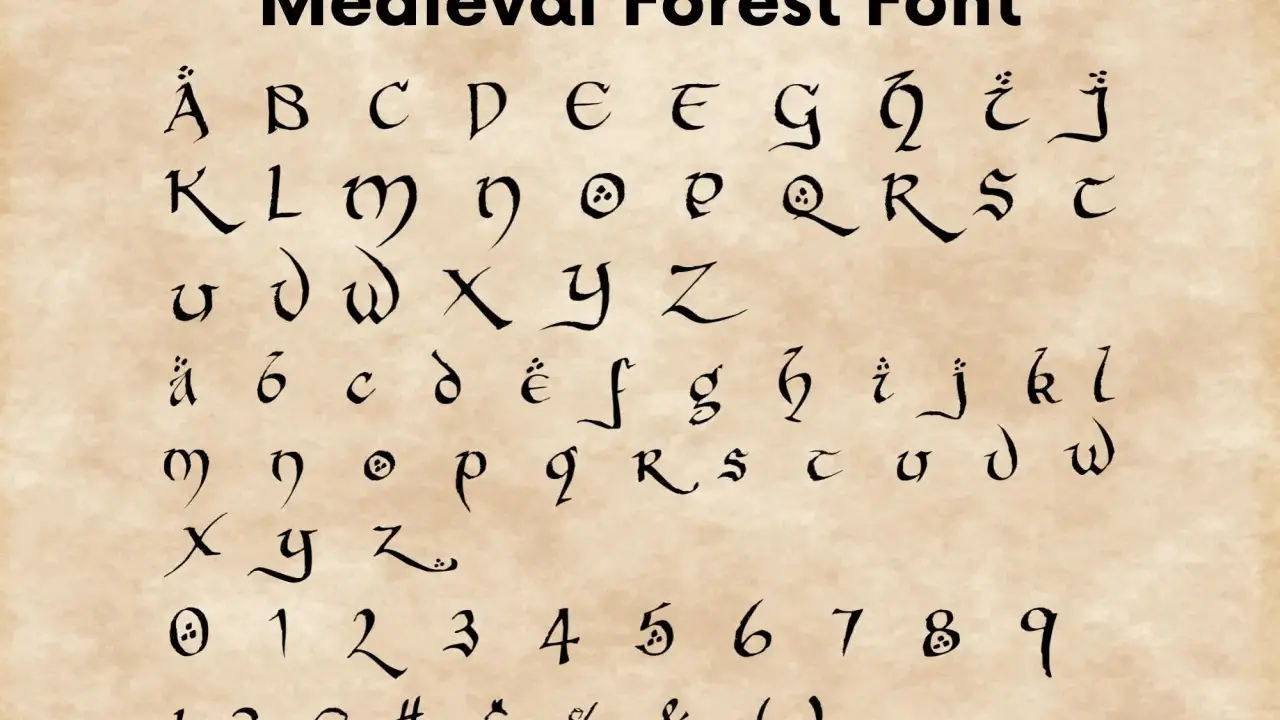
To, co potocznie bywa opisywane jako średniowieczna czcionka, w praktyce jest całym zestawem krojów inspirowanych dawnym pismem rękopiśmiennym: od ciężkich, gotyckich liter po lżejsze i bardziej dekoracyjne warianty. Taki styl potrafi od razu zbudować klimat tradycji, tajemnicy albo luksusu, ale równie szybko może osłabić czytelność, jeśli użyje się go bez wyczucia. Poniżej pokazuję, jak rozumieć ten typ pisma, czym różnią się jego odmiany i kiedy naprawdę warto po niego sięgnąć.
- To nie jeden krój, lecz cała rodzina pism inspirowanych historycznymi skryptami i gotycką tradycją.
- Najlepiej działa w krótkich hasłach, logotypach, tytułach i plakatach, a nie w długich akapitach.
- Różne odmiany dają inny efekt: od bardziej historycznego po dekoracyjny i nowoczesny.
- Przy wyborze fontu liczą się także polskie znaki, licencja i jakość odstępów między literami.
- Najczęstszy błąd to przesada: zbyt dużo ozdobników, za mały rozmiar i za długi tekst.
Czym naprawdę jest gotycki krój i skąd bierze się jego siła
W projektach użytkowych wolę mówić o kroju pisma niż o „czcionce”, bo to precyzyjniejsze, ale w praktyce sens jest prosty: chodzi o styl, który czerpie z ręcznych zapisów używanych w średniowiecznej Europie. Charakterystyczne są tu wąskie piony, ostre załamania, gęsty rytm liter i mocny, niemal rytualny obraz tekstu. To właśnie ta intensywność sprawia, że taki krój od razu niesie znaczenie, nawet zanim ktokolwiek przeczyta treść.
Ja traktuję go raczej jako narzędzie nastroju niż uniwersalny font do wszystkiego. W zależności od wariantu może komunikować sakralność, tradycję, rzemiosło, mrok, fantasy albo prestiż. Najważniejsze jest jednak to, że nie jest to jeden historyczny wzór, tylko współczesna interpretacja dawnych pism, często dostosowana do potrzeb logo, okładki, plakatu czy identyfikacji wizualnej. Kiedy już widać, że to nie jeden styl, tylko cała rodzina rozwiązań, warto porównać jej najpopularniejsze odmiany.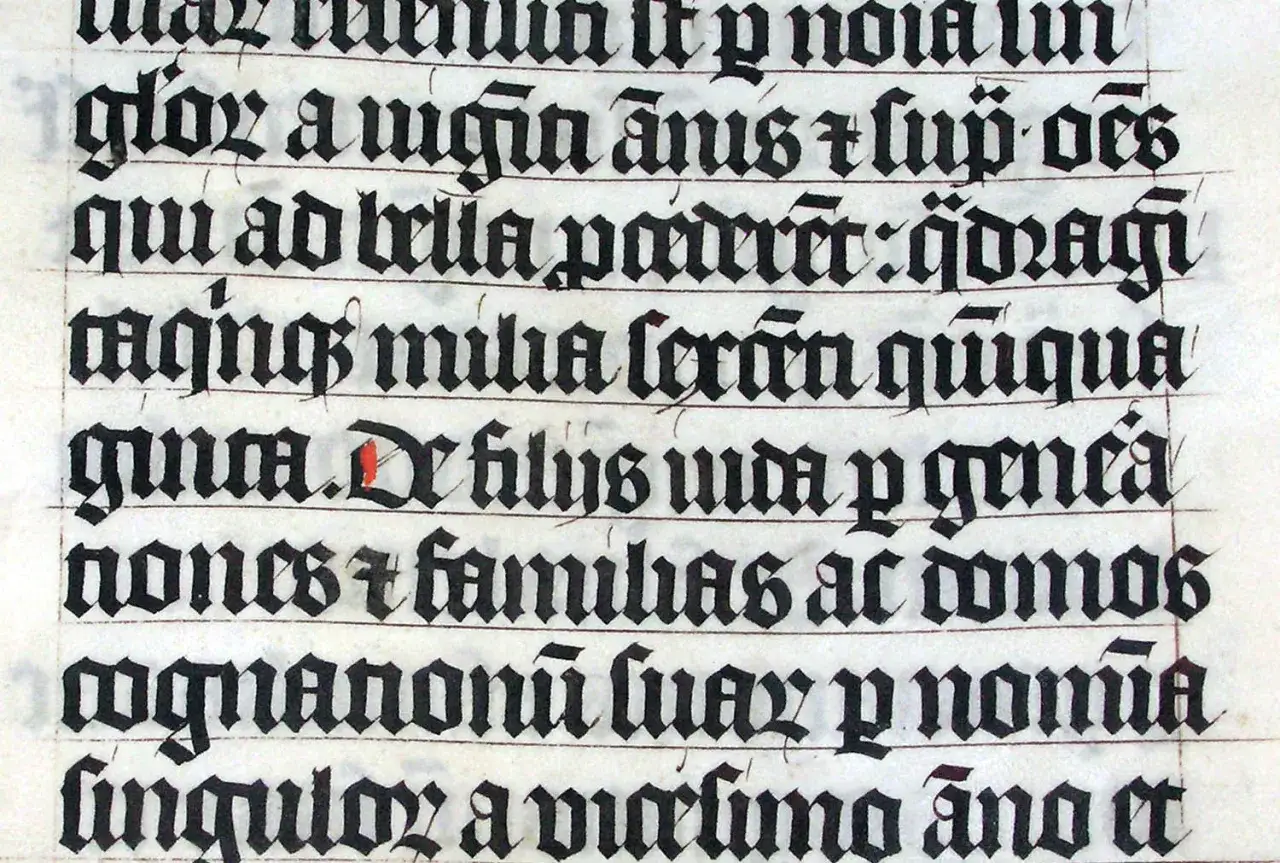
Jakie odmiany spotkasz najczęściej
Jeśli patrzysz na taki styl przez pryzmat zastosowania, łatwiej ocenić, gdzie naprawdę pracuje na komunikat marki. Poniższe odmiany różnią się nie tylko wyglądem, ale też tym, jak odbiorca odczytuje je emocjonalnie.
| Odmiana | Jak wygląda | Najlepsze zastosowanie | Na co uważać |
|---|---|---|---|
| Textura | Najbardziej pionowa, kanciasta i „gęsta” wizualnie | Historyczne motywy, certyfikaty, tytuły o mocnym ciężarze | W małym rozmiarze szybko traci czytelność |
| Fraktura | Bardziej wyrazista, z mocnym łamaniem form i wyraźnym charakterem | Logotypy, branding, plakaty, projekty z mocnym klimatem | Łatwo przesadzić z teatralnością |
| Uncjała | Miększa, bardziej zaokrąglona i spokojniejsza | Zaproszenia, projekty sakralne, książkowe detale | Może wyglądać bardziej „rękopiśmiennie” niż „gotycko” |
| Insular | Lekko odrębna, często kojarzona z tradycją wyspiarską i celtycką | Fantasy, storytelling, branding z aurą mitu | Bywa zbyt niszowa, jeśli marka potrzebuje szerokiej rozpoznawalności |
| Nowoczesny blackletter display | Współczesna, bardziej dekoracyjna interpretacja z ozdobnymi detalami | Okładki albumów, identyfikacja eventów, kraftowe opakowania | Przy nadmiarze ornamentu wygląda ciężko i chaotycznie |
Warto pamiętać o ligaturach, czyli połączeniach dwóch liter w jeden znak. W takich krojach to częsty detal, ale nie każdy font obsługuje je dobrze, więc podgląd samych liter alfabetu bywa mylący. Gdy już rozumiesz różnice między odmianami, łatwiej ocenić, w jakich projektach ten styl naprawdę pracuje, a nie tylko robi wrażenie na miniaturze podglądu.
Gdzie taki krój działa najlepiej w projektach
Nie wkładam takiego fontu do każdego projektu, bo jego największą siłą jest konkret, a nie uniwersalność. Najlepiej sprawdza się tam, gdzie sam klimat ma być częścią komunikatu i gdzie odbiorca ma od razu poczuć, że marka celowo gra historią, rzemiosłem albo mroczną estetyką.
- Logotypy i znaki firmowe - dobrze działają, jeśli marka chce wyglądać szlachetnie, tradycyjnie albo rzemieślniczo. Krótki znak z takiego kroju ma większą siłę niż długi, rozwlekły napis.
- Opakowania kraftowe i produktowe - piwo rzemieślnicze, czekolada premium, herbata, kosmetyki naturalne czy wyroby sezonowe zyskują klimat autentyczności, jeśli font nie jest zbyt agresywny.
- Plakaty, albumy i eventy tematyczne - koncert metalowy, festiwal fantasy, escape room, gra planszowa albo wydarzenie historyczne mogą dzięki niemu natychmiast ustawić ton komunikacji.
- Zaproszenia i druki okolicznościowe - szczególnie wtedy, gdy projekt ma być bardziej ceremonialny niż nowoczesny. Tu taki krój działa najlepiej w połączeniu z dużą ilością światła i spokojnym składem.
- Elementy narracyjne w grach i filmach - okładki, plansze tytułowe, nazwy lokacji czy artefaktów. W takich miejscach styl nie musi być wygodny w długim czytaniu, bo ma przede wszystkim budować świat.
Najbezpieczniej jest zacząć od dwóch wersji: jednej bardziej historycznej i jednej lżejszej, współczesnej. Porównaj je w prawdziwym layoucie, a nie na pojedynczym glifie, bo dopiero wtedy widać, czy klimat niesie treść, czy tylko udaje głębię.